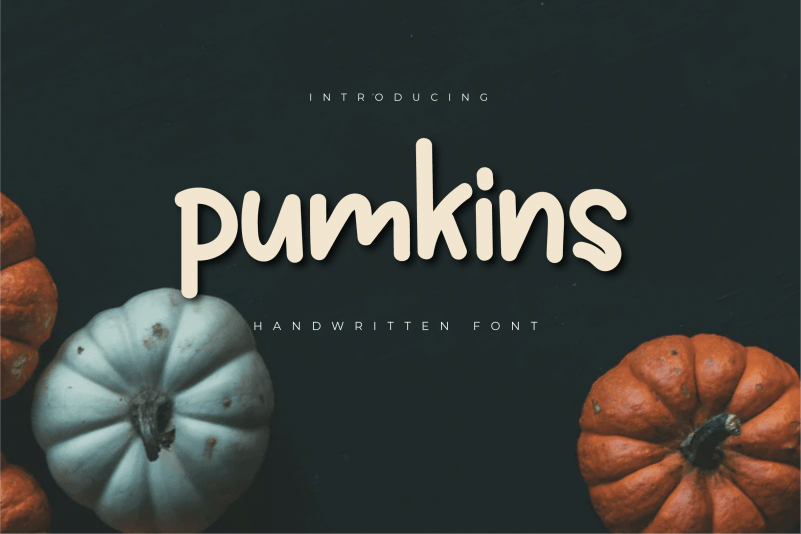
Pumkins Script Font – Download Grátis
A Pumkins Script Font é uma delicada tipografia escrita à mão, cuidadosamente criada com um toque de elegância. Embora suas linhas apresentem um estilo clássico e robusto, ainda assim mantém uma sensação amigável. É perfeita para quem busca criar designs originais e incrivelmente únicos. Este font é perfeitamente adequado para quem deseja dar um toque especial à sua identidade visual, seja em logotipos, materiais de marketing ou até mesmo letras decorativas nos seus documentos pessoais. Pumkins é uma adição fascinante ao seu arsenal de ferramentas digitais que lhe permite explorar o poder da escrita à mão digital.